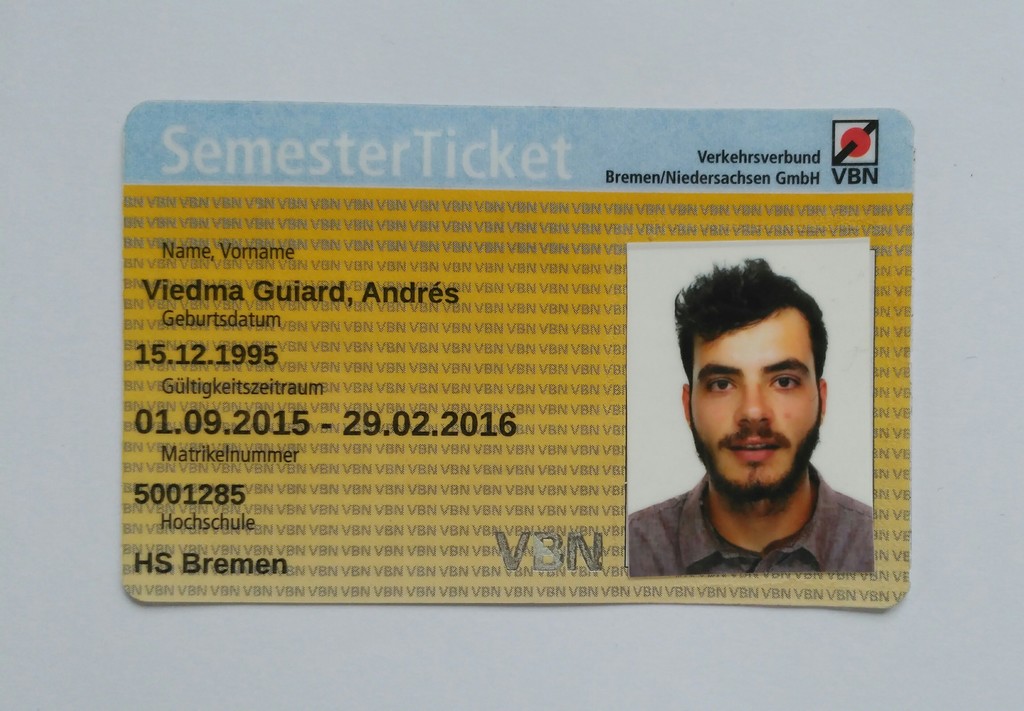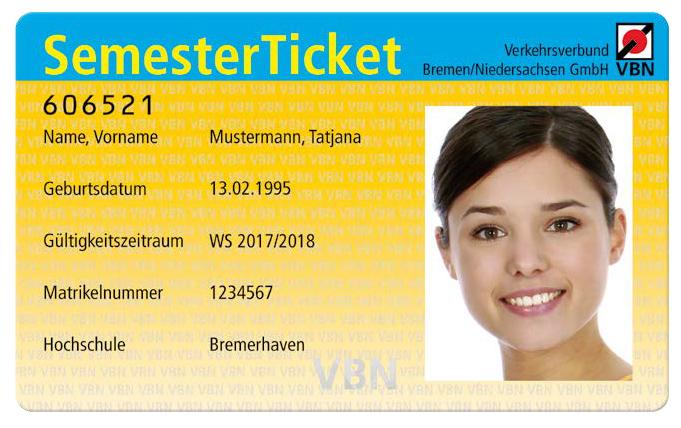
Suche Namen von Schriftart (nach einiger Recherche nicht die richtige gefunden..)
ich suche die Schriftart aus dem hier angehängten Bild. Habe schon einige Zeit gesucht, konnte allerdings nicht die exakte Font finden. Vielleicht hat sie jemand schon einmal gesehen oder weiß wo sie herkommt.
Von einem Semesterticket des VBN:
Honi soit qui mal y pense.
Yep. Ich hab nur ein Beispiel aus 2015 gefunden, leider kein aktuelles. Sollte aber reichen, um den vermuteten Bösewicht zu enttarnen 8-).
Vielen Dank für die Antworten. Wie bereits vermutet geht es tatsächlich um das Semesterticket, allerdings soll nur ein möglichst echtes Duplikat für ein Video erstellt werden, in dem dieses verbrannt wird. Mit Details verschone ich euch, kann aber versprechen, dass es nicht für illegale Zwecke genutzt wird (wüsste auch nicht wie man die anderen Merkmale fälschen soll :D ). Da es ja aber scheinbar verschiedene Fonts auf den Semestertickets gibt, kann man ja auch andere nehmen, das wusste ich nicht.
Ein aktuelles Ticket sieht übrigens so aus:
Die Nummer ist aus der "OCR B"
Die Schrift sieht mir nach "Frutiger Condensed" aus
Das hättest Du für uns Bedenkenträger aber gleich schreiben sollen. Bzgl. der anderen Schriften würde ich da Einschränkungen vornehmen. Die Formulartschrift scheint immer eine Frutiger Condensed zu sein, nur ausgefüllt wird nach Lust und Lilalaunebär. Daher würde ich zuerst nach eine schmalen Grotesk im Frutiger-Style suchen. Hmmm ... Video? Künstler? Das schreit nach leeren Kassen, die durch das Semesterticket noch weiter ausgesaugt werden. Also sollte es eine freie Schrift sein? Opti Franz 55 und 65 wären eine Frutiger Condensed und frei aus dem Internet zu beziehen: http://opti.netii.net/fonts-f/index.htm
Das Ausfüllen muss ja gar nicht realitätsgetreu sein. Nachdem das Semesterticket verbrannt wird habe ich da eine Gegenfrage: Soll die Indentität auf dem Ausweis vom Zuschauer erfasst werden? Wenn ja: Dann würde ich ganz fett und aufdringlich, gut sichtbar mit einer OCR-B, Letter Gothic oder sonst was „alternativ realem“ ausfüllen. Eine freie OCR-B habe ich nicht in der Liste.
Aber wie wäre es mit einer Letter Gothic? Die gibt es in einigen Versionen, z.B. von URWPP, frei inkl. für kommerzielle Nutzung. Die wird mit einigen Versionen von Ghostscript mitgeliefert ...
Oder was ganz anders? Carrois Gothic: https://www.fontsquirrel.com/fonts/carrois-gothic
Wer kennt eine freie und für solche Anwendungen halbwegs brauchbare OCR-B? Und vielleicht auch noch eine OCR-A dazu? Und das ganze natürlich mit den Umlauten und Akzenten für die großen europäischen Sprachen?
Ohne auf Brauchbarkeit getestet zu haben: http://ansuz.sooke.bc.ca/page/fonts#ocrb. Unter den großen europäischen Sprachen sollte deutsch und die skandinavischen Sprachen gehen, französisch, und ungarisch wohl nicht, von griechisch oder russisch ganz zu schweigen. (In der OCRB.otf definierte Sonderzeichen jenseits des ASCII-Bereichs sind ¡¿ÄÆÖØÜßäæöøüıŒœȷ, eine Hand voll (nicht alle) griechischer Großbuchstaben und diverse nichtkombinierbare Diakritika)